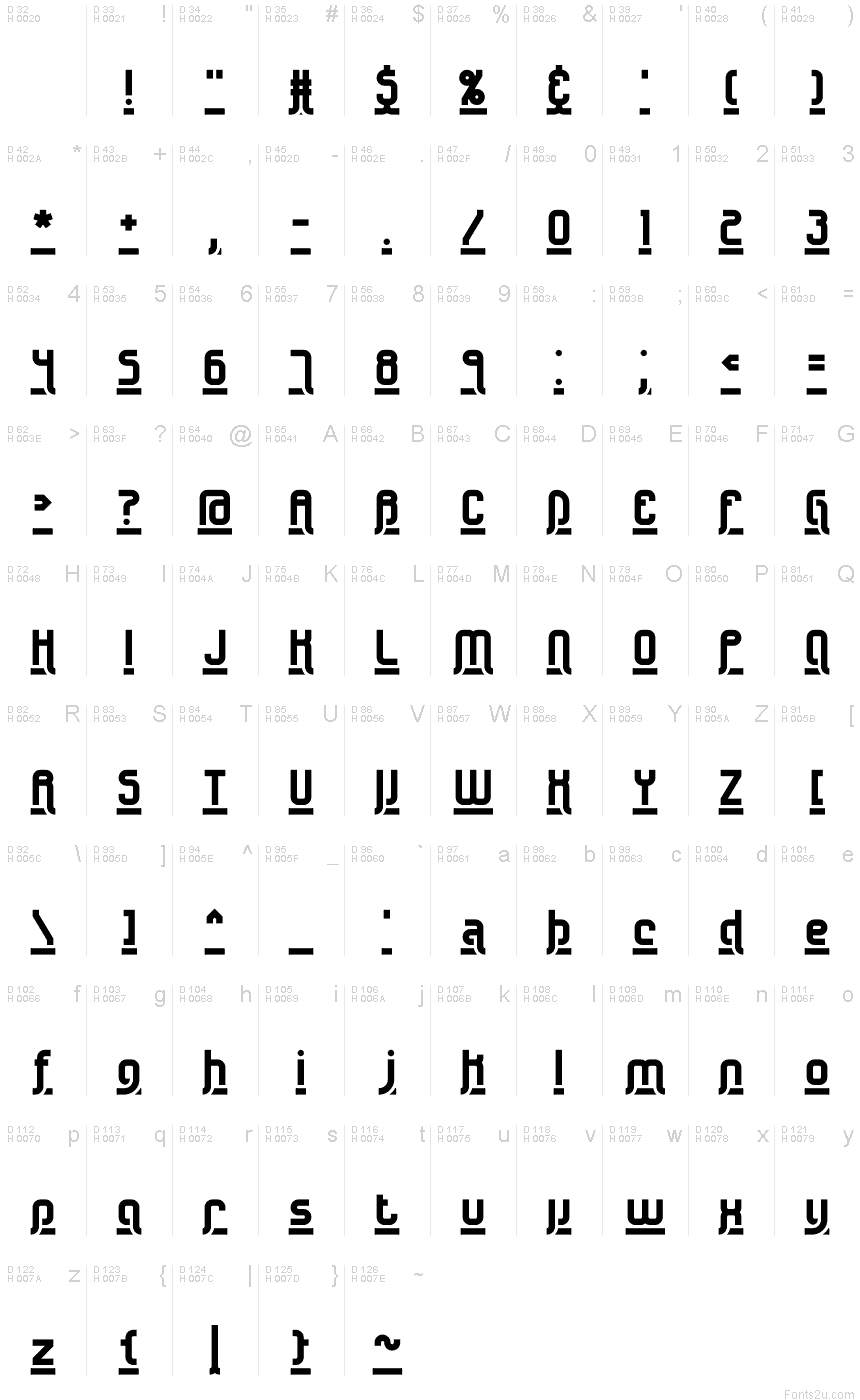
Underscore 2 BRK
يعد خط Underscore 2 BRK من AEnigma Fonts خط عرض مجانياً بأسلوب «جروفي» (groovy) مع لمسة أنيقة تعود لعصر الفضاء في أواخر الستينيات. تم بناء الحروف من ضربات سميكة ومستديرة مع انحناءات عمودية عميقة تنتهي بخطافات ناعمة، مما يمنح الخط ككل إيقاعاً انسيابياً يشبه طراز «اللو رايدر» (low-rider)، بعيداً عن الجمود الهندسي الصارم.
يعمل هذا الخط بشكل رائع في منشورات الحفلات الموسيقية، وملصقات النوادي، والعلامات التجارية ذات الطابع القديم (ريترو)، وأغلفة المجلات، وعناوين التصميم، حيث يمكن لبضع كلمات أن تبرز هذا المظهر الانسيابي. وبما أنه خط مجاني، فهو مناسب أيضاً للشعارات والعناوين القصيرة على الويب، خاصة عندما تريد أن تقوم الأشكال الممتدة لأسفل بضبط الجانب الجمالي نيابة عنك.